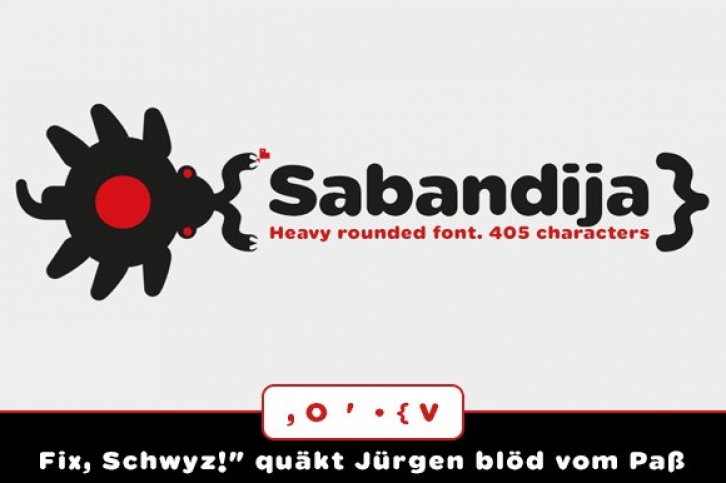
Nueva tipografía veraniega de formas voluptuosas, gruesas y redondeadas. Fuente de talla baja de carácter amigable con ascendentes y descendentes cortos de fuerte contraste en las uniones de las astas, agradable y funcional para títulos y textos cortos o el diseño de carteles y posters.
New summer typography voluptuous, thick and rounded shapes. Source of stunting friendly character and falling short of strong contrast in the joints of the antlers, pleasant and functional for titles and short texts or designing posters and affiches.